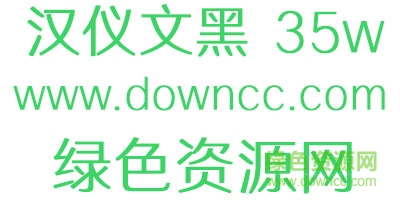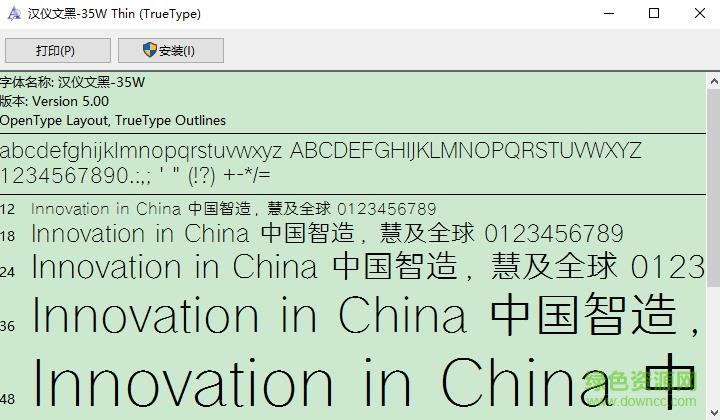
漢儀文黑 35w thin字體
漢儀文黑 35w是一款非常實(shí)用的經(jīng)典字體,這款漢儀字體結(jié)構(gòu)端正大方,筆畫粗細(xì)均勻,清晰易讀,整體效果非常不錯(cuò),歡迎大家來綠色資源網(wǎng)下載體驗(yàn)!
漢儀文黑 35w
漢儀文黑字體特點(diǎn)
西文設(shè)計(jì)
漢儀文黑的西文設(shè)計(jì)沿用了與著名字體helvetica和Univers相同的Neo-grotesque字形風(fēng)格。Neo-grotesque類字形簡(jiǎn)潔勻質(zhì)硬朗,可以與旗黑的中文部分達(dá)成非常良好的配合。
結(jié)構(gòu)設(shè)計(jì)
UD設(shè)計(jì)盡可能減少多余的修飾元素,將除字形識(shí)別以外的信息量將至最低,盡可能避免過大的弧度為閱讀所帶來的不穩(wěn)定感,更方便視覺障礙者的閱讀。
筆畫設(shè)計(jì)
設(shè)計(jì)簡(jiǎn)約、爽朗富有時(shí)代氣息固然重要,但我們?cè)谠O(shè)計(jì)時(shí)不能忘卻字的民族性和傳統(tǒng)文化,筆劃必須要有內(nèi)涵。筆畫設(shè)計(jì)中融入了書寫的韻味,采用“陰陽線”的處理方法,講究線條之美,使筆劃挺拔有力,剛?cè)嵯酀?jì)。通過筆畫的粗細(xì)變化,賦予字體不同的性格與表現(xiàn)力,但“骨子里”卻是“一家人”,線條勁道,緊致。